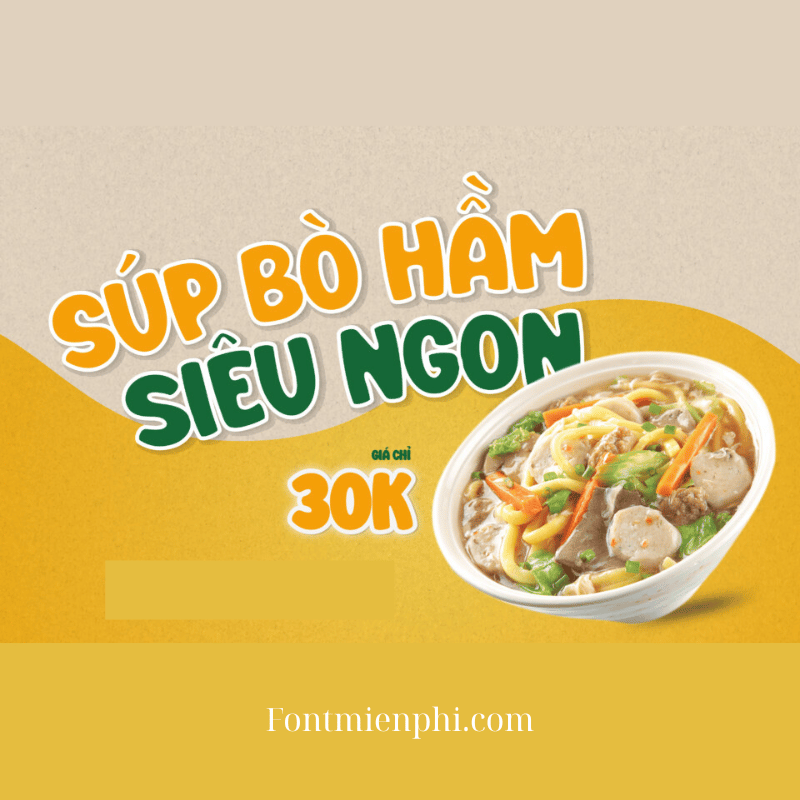
Font Việt hóa 1FTV VIP Super Boys
Font Việt Hóa 1FTV VIP Super Boys – Phong Cách Độc Đáo Cho Thiết Kế
Giới Thiệu
Font Việt hóa 1FTV VIP Super Boys là bộ font chữ nghệ thuật độc đáo, được thiết kế dành riêng cho các dự án sáng tạo. Với phong cách trẻ trung, cá tính, font chữ này phù hợp cho thiết kế poster, banner, logo, và các ấn phẩm quảng cáo. Đây là lựa chọn hoàn hảo để tạo điểm nhấn ấn tượng trong mọi thiết kế.
Đặc Điểm Nổi Bật
• Thiết kế độc đáo: Nét chữ bo tròn, cách điệu, mang phong cách “Super Boys” trẻ trung, mạnh mẽ.
• Hỗ trợ tiếng Việt: Font được Việt hóa đầy đủ, đảm bảo hiển thị rõ ràng, sắc nét với mọi ký tự có dấu.
• Đa dạng ứng dụng: Phù hợp với nhiều lĩnh vực như game, thời trang, âm nhạc, quảng cáo.
Tại Sao Nên Chọn 1FTV VIP Super Boys?
Font chữ này không chỉ giúp thiết kế của bạn trở nên khác biệt mà còn truyền tải thông điệp mạnh mẽ, thu hút người xem. Đây là font chữ được giới designer ưa chuộng nhờ tính ứng dụng cao và phong cách độc nhất.
Kết Luận